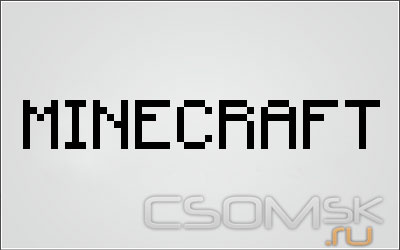
шрифт майнкрафт для фотошопа
Шрифт исполнен в стиле популярной игры Minecraft. Хорошо подходит для создания логотипов в данном стиле. Надписи можно реально приблизить в стиль игры если ему задать определенное оформление.
Пример:
Задан в фотошопе стиль шрифту с текстурой